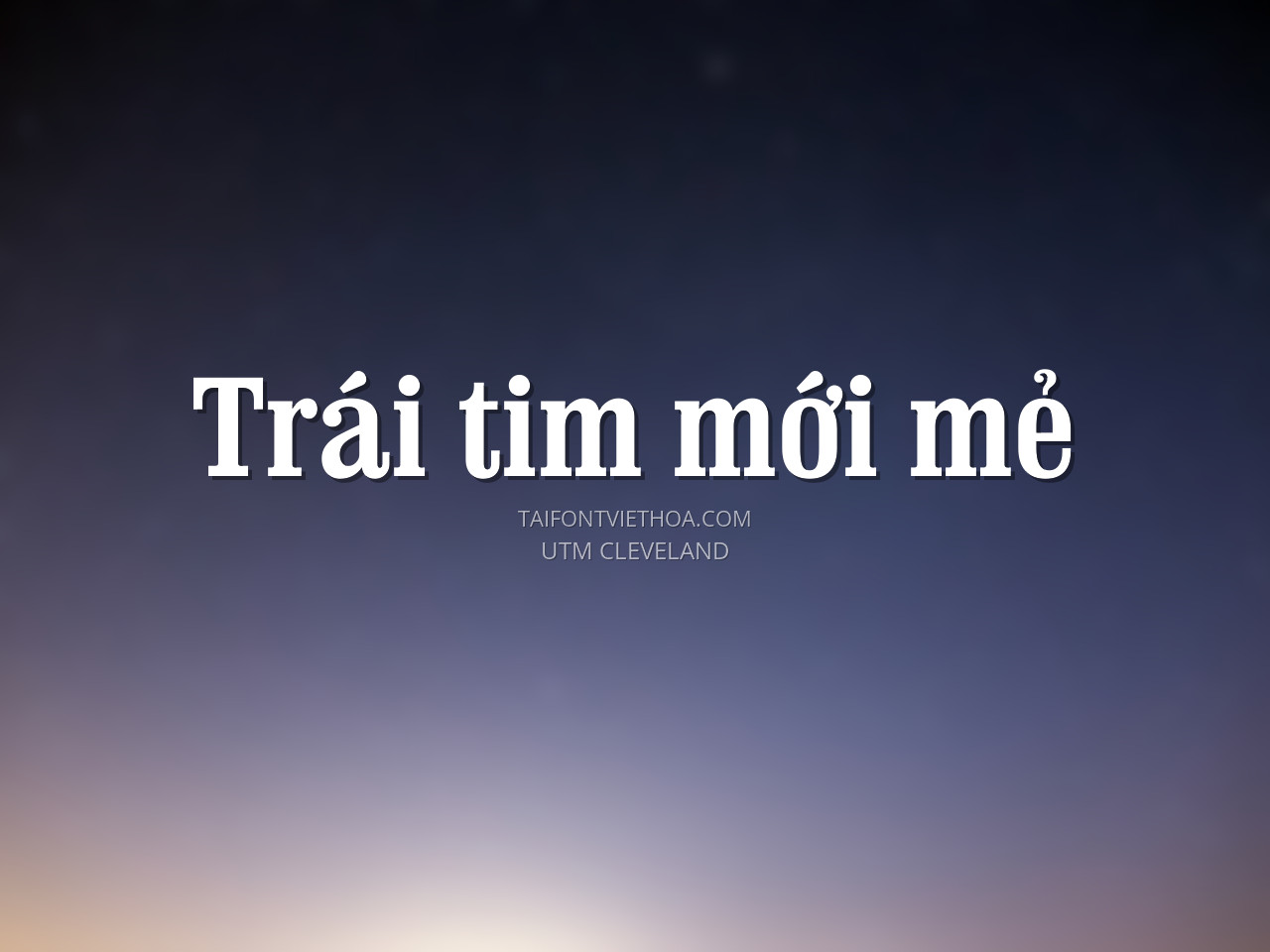
Font việt hóa UTM Cleveland
Giới thiệu về font UTM Cleveland
UTM Cleveland là phiên bản Việt hóa của font Cleveland – một kiểu chữ slab serif hiện đại và mạnh mẽ, được thiết kế để mang đến sự chắc chắn và cá tính trong các dự án thiết kế. Font gốc nổi bật với các nét chữ dày, vuông vức và chân chữ đặc trưng, tạo nên vẻ ngoài nổi bật và dễ nhận diện. Phiên bản Việt hóa đã được hoàn thiện để hỗ trợ đầy đủ tiếng Việt cùng hơn 200 ngôn ngữ khác, mở rộng khả năng sử dụng trong các dự án đa dạng.
Đặc điểm thiết kế và ứng dụng của UTM Cleveland
UTM Cleveland sở hữu cấu trúc slab serif với các nét chữ dày, vuông vức và chân chữ rõ nét. Font có thiết kế chắc chắn, dễ đọc và tạo hiệu ứng thị giác mạnh mẽ, rất phù hợp cho tiêu đề, logo và các thiết kế cần sự nổi bật. Font còn được trang bị nhiều ligature và glyph thay thế giúp tăng tính linh hoạt trong thiết kế.
Font thích hợp sử dụng trong thiết kế poster, bảng hiệu, nhận diện thương hiệu, quảng cáo và các dự án truyền thông đa phương tiện. Các ngành nghề phù hợp gồm: quảng cáo, thời trang, công nghệ, sự kiện và truyền thông sáng tạo.